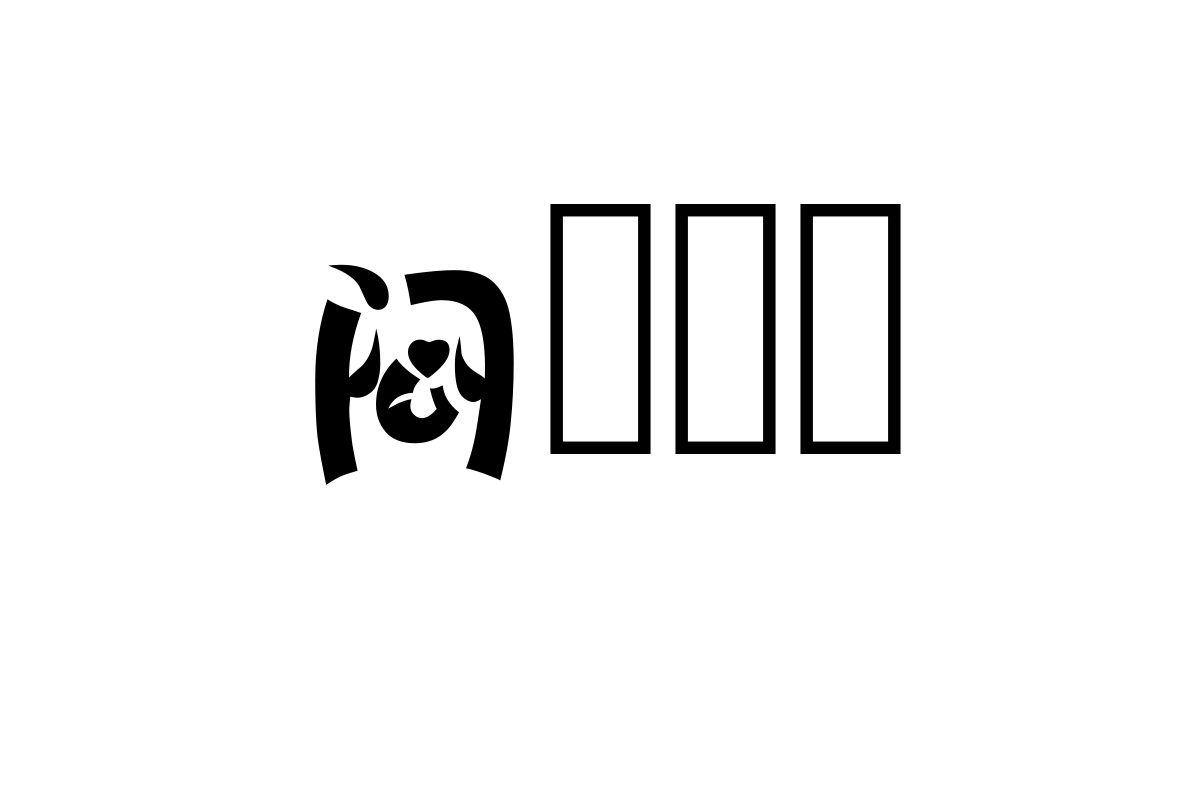
汉仪象形兰体是一种具有中国传统风格的字体,它以兰花为灵感来源,将兰花的形态和线条融入到字体设计中。这种字体的特点是线条流畅,结构简洁,具有很强的视觉冲击力和艺术感。
汉仪象形兰体的特点包括:
1. 线条流畅:汉仪象形兰体的线条非常流畅,给人一种优雅、自然的感觉。
2. 结构简洁:汉仪象形兰体的结构非常简洁,每个笔画都经过精心设计,使得整体看起来更加和谐、统一。
3. 艺术感强:汉仪象形兰体具有很强的艺术感,无论是在字体大小、间距还是整体布局上都展现出一种独特的美感。
4. 适合多种应用场景:汉仪象形兰体适用于各种场景,如标题、正文、广告、海报等,都能展现出其独特的魅力。
总之,汉仪象形兰体是一种极具中国特色的字体,它以其独特的风格和艺术感受到了广泛的欢迎。